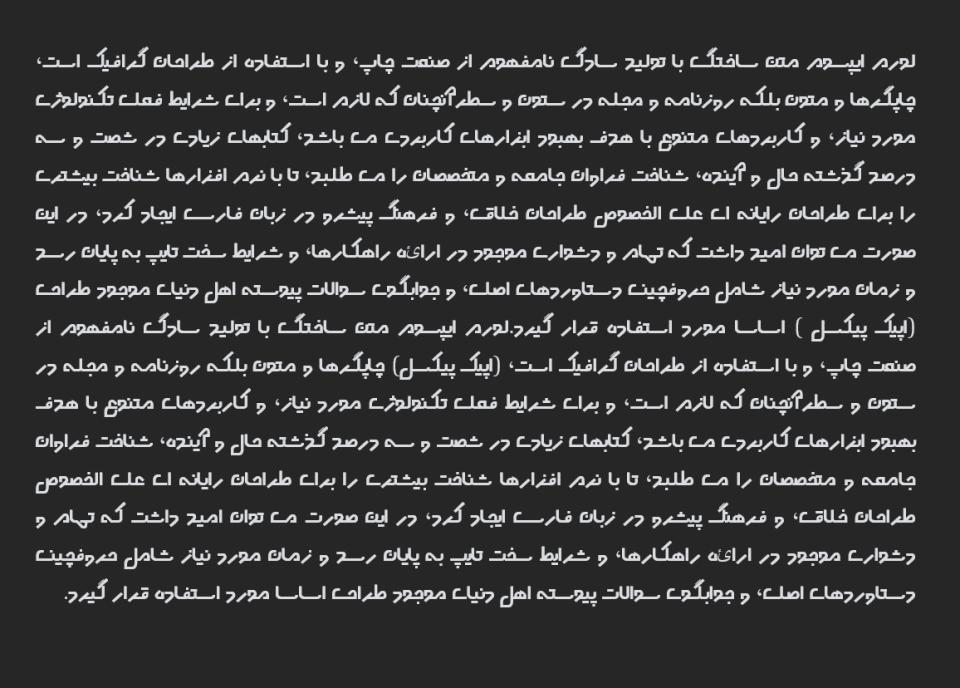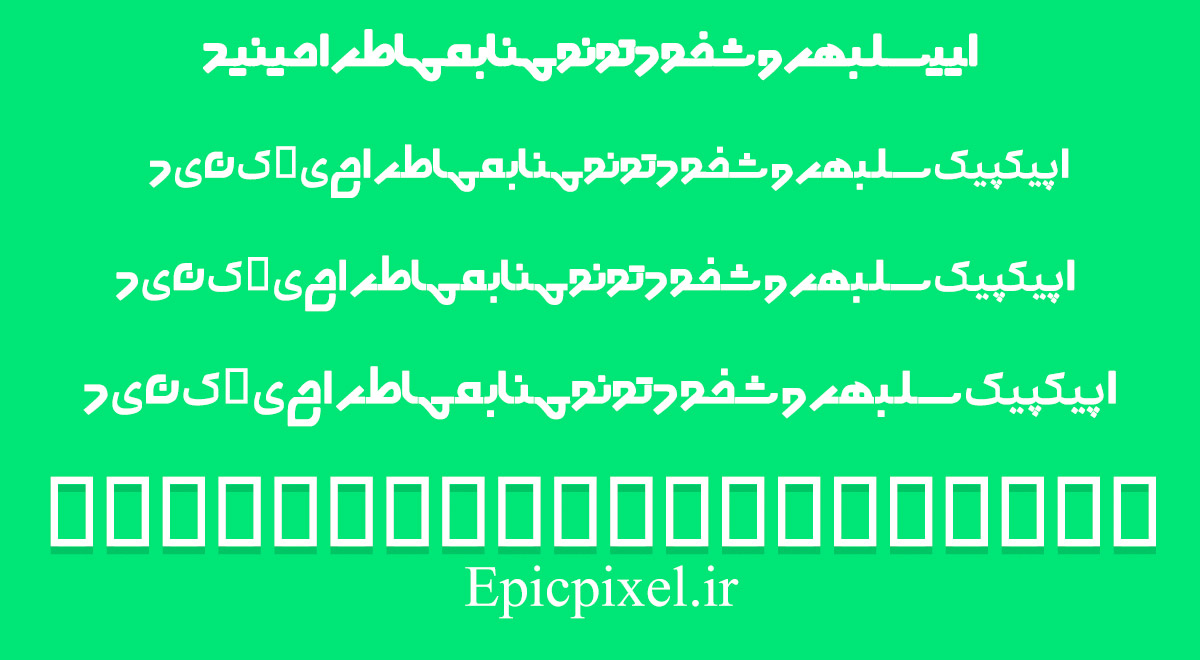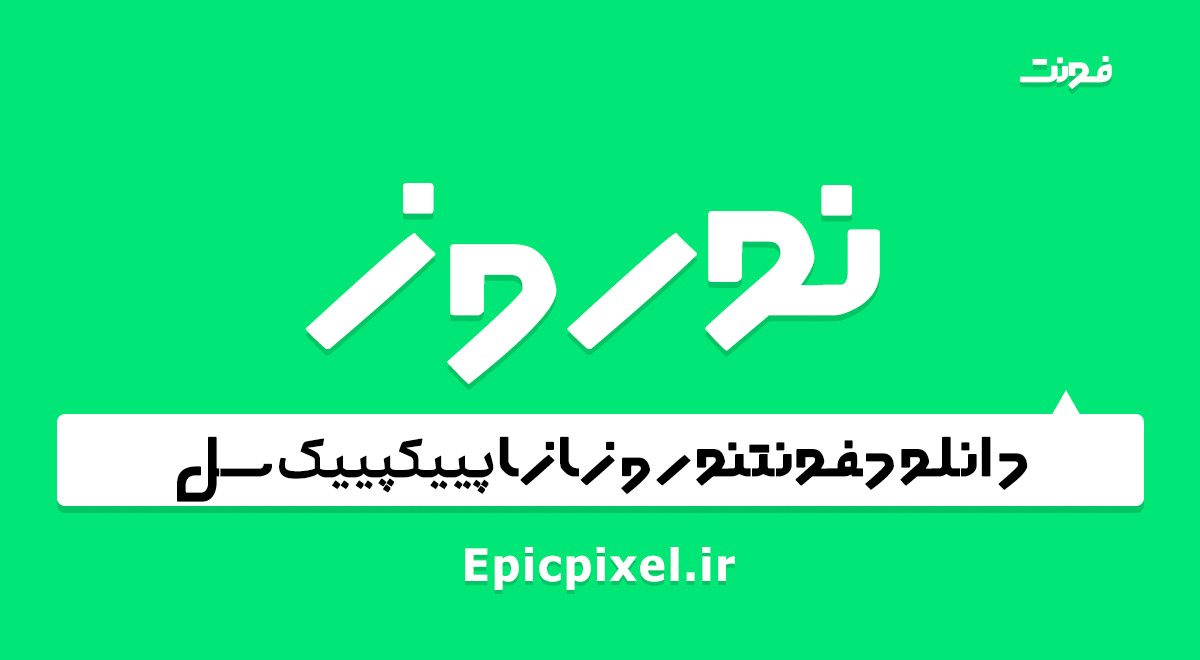
فونت نوروز فارسی
فونت نوروز فارسی برای کسانی که به دنبال تلفیقی از زیبایی و کارایی هستند، یک انتخاب بی نظیر است. این فونت با طراحی چشم نواز و خوانایی بالا، هم در متون چاپی و هم در صفحات وب عملکردی عالی دارد. طراحی حرفه ای و تناسب زیباشناسانه آن به نوشته هایتان جلوه ای خاص می بخشد، در حالی که خوانایی آن از خسته کننده بودن چشم جلوگیری می کند. نکته مثبت این فونت رایگان بودن آن است که باعث می شود بدون هیچ هزینه ای از مزایای آن بهره مند شوید.
ویژگی های بارز فونت نوروز شامل تنوع در ضخامت حروف و استایل های مختلف است که انعطاف پذیری بالایی را برای استفاده در پروژه های مختلف فراهم می آورد. همچنین این فونت با تمامی سیستم عامل ها و نرم افزارهای طراحی سازگاری کامل دارد، بنابراین هیچ محدودیتی در استفاده از آن نخواهید داشت. اما توجه داشته باشید که این فونت، به دلیل طراحی خاص، ممکن است در متون بسیار طولانی و رسمی کمی نامناسب به نظر برسد.
فونت خیلی عجیبیه ولی برای کارها و متن های طولانی به درد نمیخوره